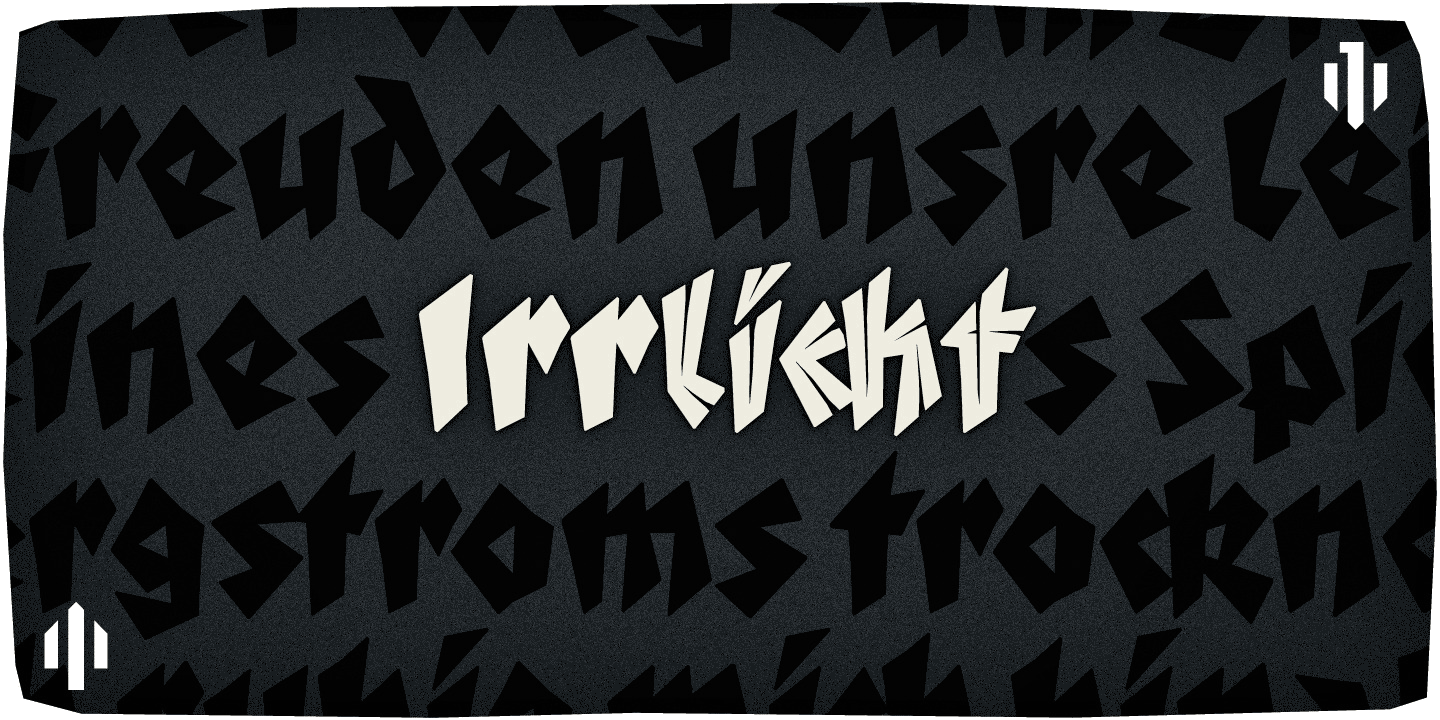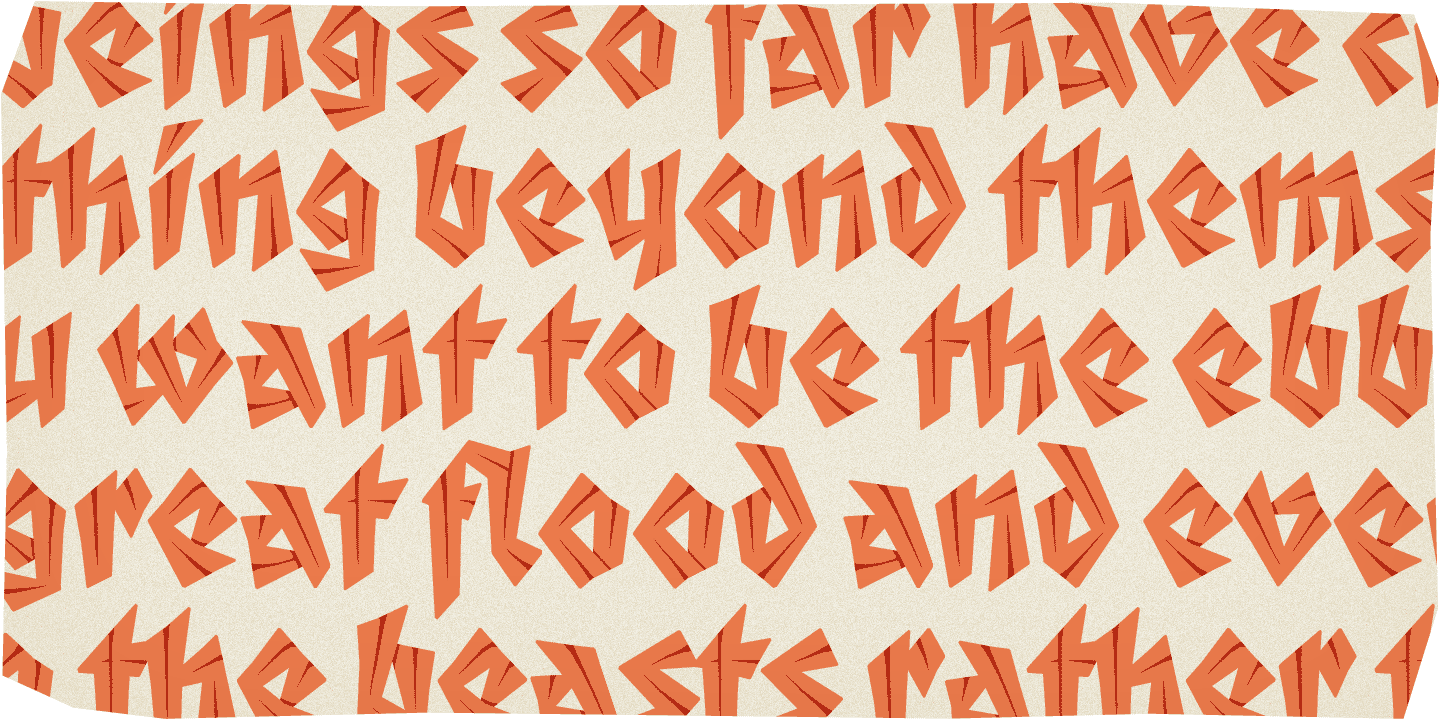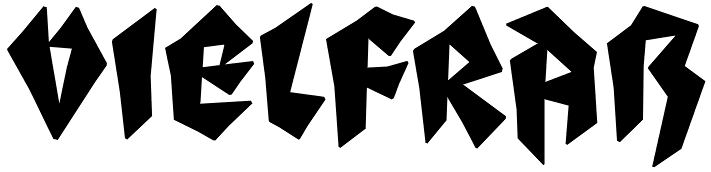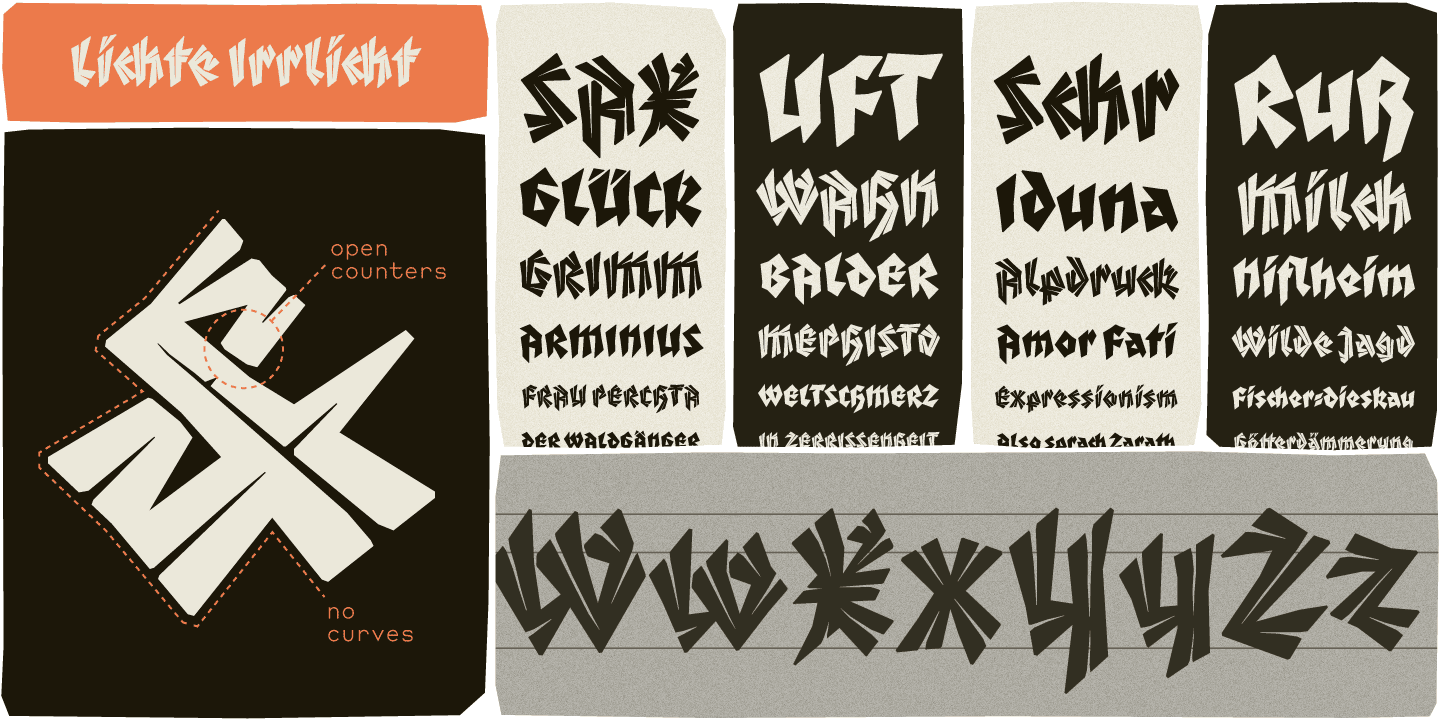
- Gebrochene Schrift
- Versaleszett:
- enthalten
Die Irrlicht von Ari Hausel ist eine digitale Version der C.H. Kleukens Judith Type. Die gebrochene, holzschnittartige Schrift entstand im Original 1923 für biblische Drucke der Ernst-Ludwig-Presse. Das erste Werk, das Buch Judit, gab der Schrift ihren Namen.
Neben der Digitalisierung des Grundschnitts (»Irrlicht Dunkle«) entstanden auch eine Schablonenvariante und eine lichte Version. Beide sind im Schnitt Irrlicht Lichte vereint.